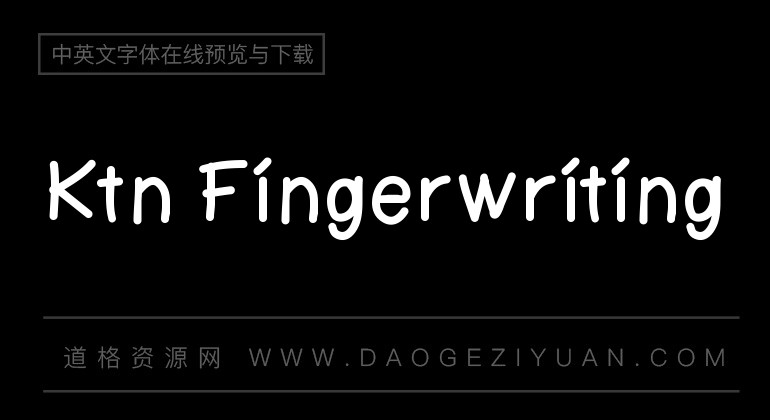
? Ktn Fingerwriting 是一款手写风格的字体,由日本设计师Ktn创作。它具有清爽、自然、活泼的特点,特别适合用于节日、活动、婚礼等场合的卡片、海报等设计中。Ktn Fingerwriting 字体的笔画自然,字体比较瘦,适合用来表达温柔的情感,有时也可用来表达活泼的心情。内容介绍
Ktn Fingerwriting是一款非常不错的手写艺术字体,具有很好的视觉感,适合于文化类的宣传设计、商业类品牌的广告和产品包装设计以及个性化文字排版等较多场景。